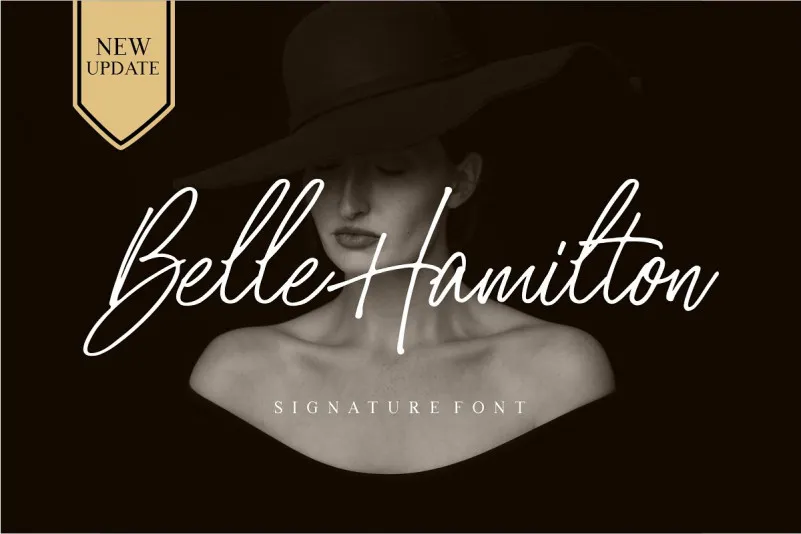
Belle Hamilton Font Duo – Download Grátis
Descubra Belle Hamilton Font Duo, uma elegante escolha para designers que valorizam a sofisticação contemporânea com um toque refinado e natural. Esta fonte Script é ideal para criar layouts de design gráfico incrivelmente profissionais, desde artigos de cartaz até etiquetas em produtos. Com sua combinação perfeita de serif e estilo de assinatura, Belle Hamilton não só oferece beleza elegante, mas também permite uma aplicação versátil e multifacetada para diferentes projetos, como cartões de visita, logotipos, embalagens de produto ou cabeçalhos de página. Ela está disponível com letras maiúsculas e minúsculas, números, pontuação e caracteres multilíngue, tornando-a uma fonte versátil para designers experimentarem em seu próximo projeto. Composta por M.0Type, Belle Hamilton é definitivamente uma escolha inteligente para qualquer designer buscando um toque de sofisticação no design editorial ou gráfico.